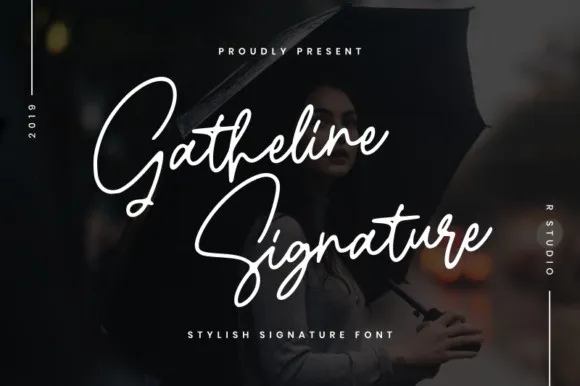
Gatheline Signature Font
Olá! Gatheline é uma fonte cíliar e elegante desenvolvida pela 1001fonts. Esta fonte inclui alternativas de minúsculas e ligaturas, permitindo que você personalize facilmente o seu texto para adicionar um toque autêntico e sofisticado. Com Gatheline Signature Font, é fácil transformar qualquer ideia de design em algo único e único com apenas alguns cliques. Esta fonte cíliar foi projetada para ser usada no ambiente digital e impresso, idealmente para uso em eventos especiais como casamentos ou festas de aniversário, embalagens, cartazes, sinos, logotipos, marcas e outros veículos de mídia. Ela é a escolha perfeita para estilos que valorizam a elegância e sofisticação dos traços da escrita à mão, tornando-a uma ótima adição para qualquer projeto visual.